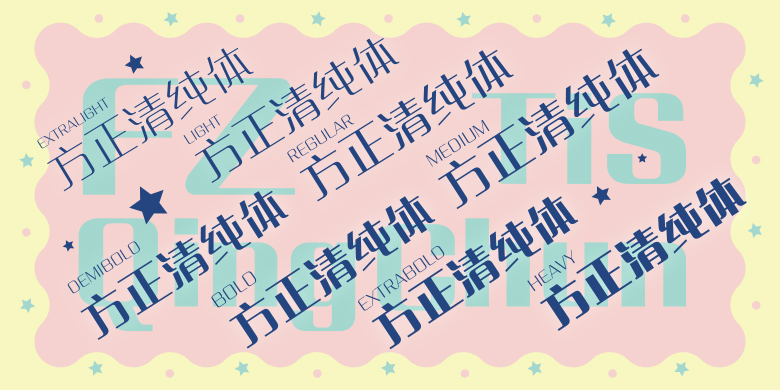
品牌:方正字库设计师:郭炳权发行时间:2016字库编码:大陆简体(GB2312-80)、简繁扩展(GBK)、港台地区(BIG-5)分类:创意字体
方正清纯体系列
方正清纯体是一款运用几何法设计的创意字体。其笔画对比明显,横细竖粗,折笔处均为圆弧形,撇、捺笔画对称。方正清纯体家族包含8款字重,气质温婉、清新,宛若清纯可人的少女,适用于女性类服饰、日化、家居品牌的广告和产品包装设计。